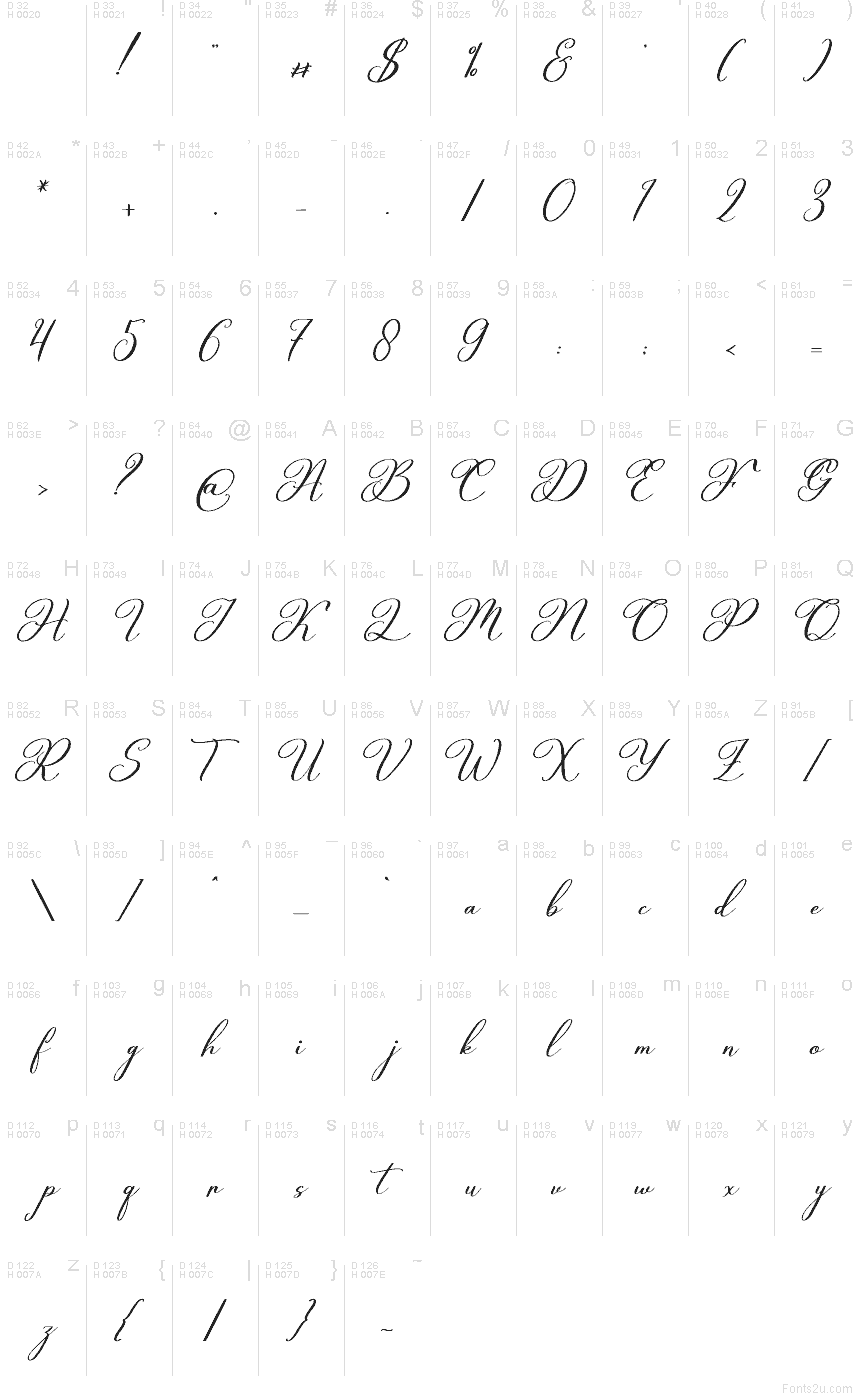
Celtaniya Bioffany od Gracetype Studios je bezplatné kaligrafické písmo definované dlouhými smyčkami a plynulým rytmem s vysokým kontrastem. Velká písmena se otevírají do širokých oválných tvarů, zatímco malá písmena si udržují lehčí a hravější tempo, což dodává písmu formální nádech, aniž by působilo stísněně.
Tato kombinace skvěle vynikne na svatebních oznámeních, v brandingu luxusních značek, u podpisových log, citátů na sociálních sítích nebo na obalech, které vyžadují elegantní nadpisy. Prodloužené tahy a vzdušné křivky dodávají krátkým názvům a frázím slavnostní tón, zejména v místech, kde by běžné písmo působilo příliš obyčejně.